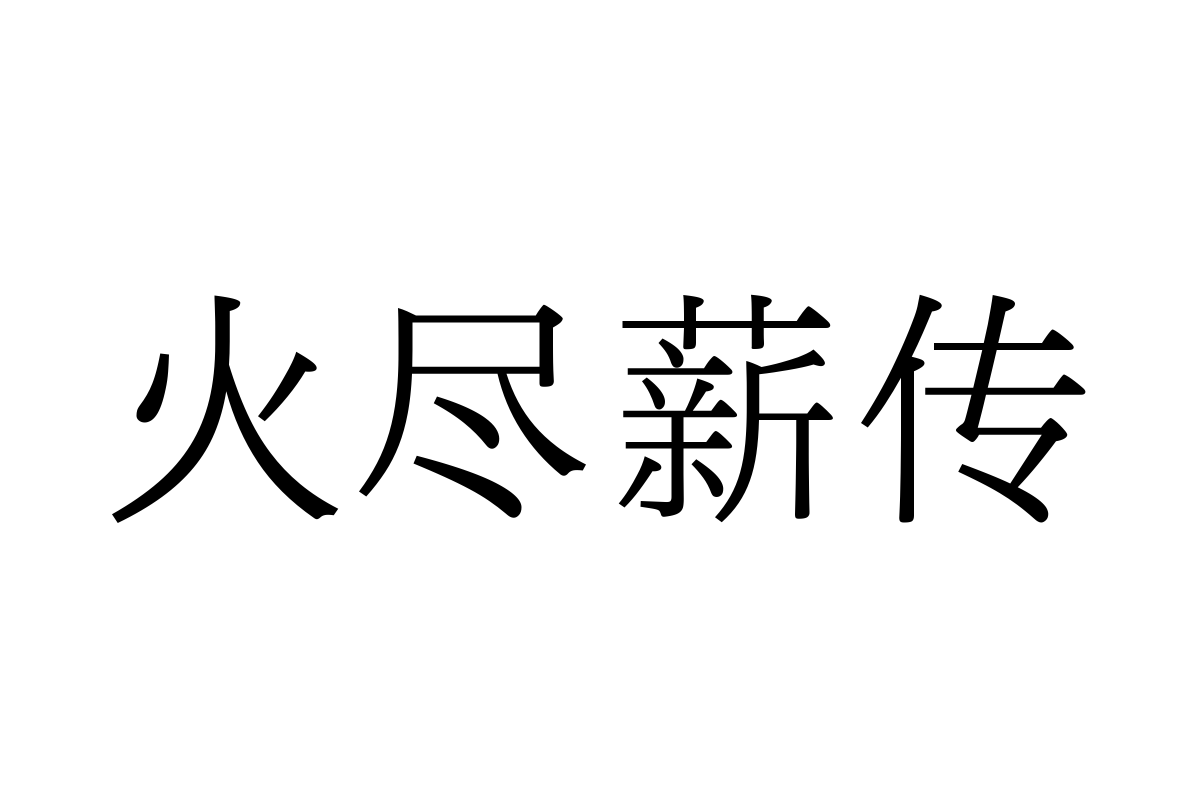
汉仪玄宋 35S 字体是一款具有现代感和艺术气息的中文字体,适用于各种商业、广告、设计等领域。这款字体的特点是线条流畅、结构简洁,给人一种清新、自然的感觉。其笔画粗细适中,既有力度又有柔美,适合用于标题、正文等多种场景。同时,汉仪玄宋 35S 字体还具有良好的可读性和辨识度,无论是在印刷还是电子屏幕上都能展现出良好的视觉效果。